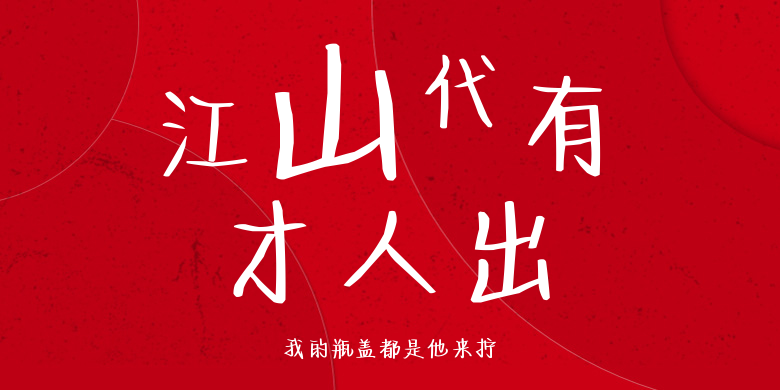
我的瓶盖都是他来拧
我的瓶盖都是他来拧,这款字体结构工整、笔画清晰,兼顾美观与易读性,适用于标题、正文、海报、包装、LOGO 等多种场景。字形优雅稳定,风格百搭耐看,适配日常排版与创意设计,让文字呈现更舒适、更具质感。我的瓶盖都是他来拧一笔一画,皆是细节,以均衡的比例、流畅的线条打造舒适视觉体验,字形端正大气,风格简约现代。无论是商业设计、品牌宣传还是日常排版,都能轻松驾驭,让文字更有格调与力量。我的瓶盖都是他来拧字体下载。